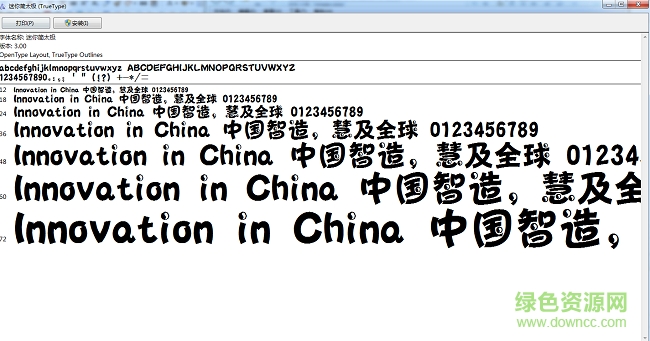
Jtaiji是什么字體?jtaiji字體是一款ttf格式的迷你簡太極藝術(shù)字體,張弛有度,圓潤大方,每一個點(diǎn)都是黑白相間的太極符號,非常特別,適合朋友們在進(jìn)行廣告海報等詞面設(shè)計的時候使用,即有亮點(diǎn)又突出,喜歡的小伙伴趕緊下載收藏吧!
迷你簡太極字體是一款柔中帶剛,又灑脫不羈、隨心所欲,有點(diǎn)兒像舞太極,讓人一看字中蘊(yùn)含著力道,取了太極剛?cè)岵?jì)的精華,將舒展優(yōu)美、動作和順、平正樸實(shí)的太極文化融入書法當(dāng)中!